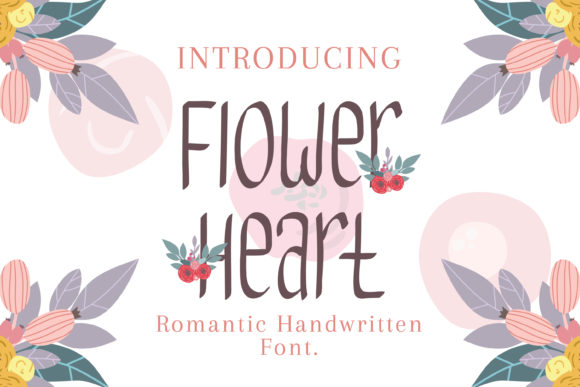
Flower Heart
Se stai cercando risorse di alta qualità come Flower Heart, questo pacchetto premium è una scelta fantastica per i tuoi progetti creativi.
Che tu stia creando prodotti POD (Print on Demand), partecipazioni di nozze o grafiche per i social media, Flower Heart è la scelta ideale.